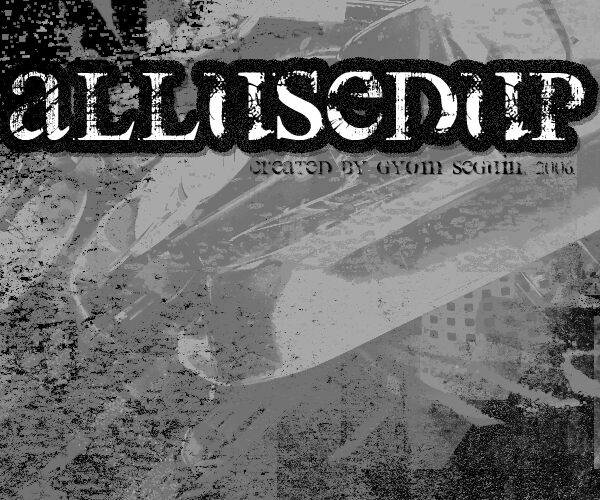
All Used Up to darmowy, "zniszczony" krój displayowy, który wygląda, jakby został przeciągnięty po betonie i zbyt wiele razy skserowany. Litery sprawiają wrażenie kruchych i porysowanych, z poszarpanymi krawędziami i nierówną, "wytartą" teksturą, co natychmiast dodaje im wieku, surowości i napięcia. To krój głośny, surowy i nieco chaotyczny, dzięki któremu nawet jedno słowo nabiera charakteru podartego plakatu na starym murze z cegły.
All Used Up świetnie sprawdzi się, gdy chcesz nadać wyrazisty klimat plakatom koncertowym, tytułom horrorów lub thrillerów, logotypom gier dystopijnych, okładkom zinów, brandingowi odzieży streetwearowej czy postarzanym opakowaniom. Ten darmowy font najlepiej prezentuje się w dużym rozmiarze, eksponując każde pęknięcie i lukę – w mniejszych tekstach najlepiej łączyć go z czystym, prostym krojem bezszeryfowym.